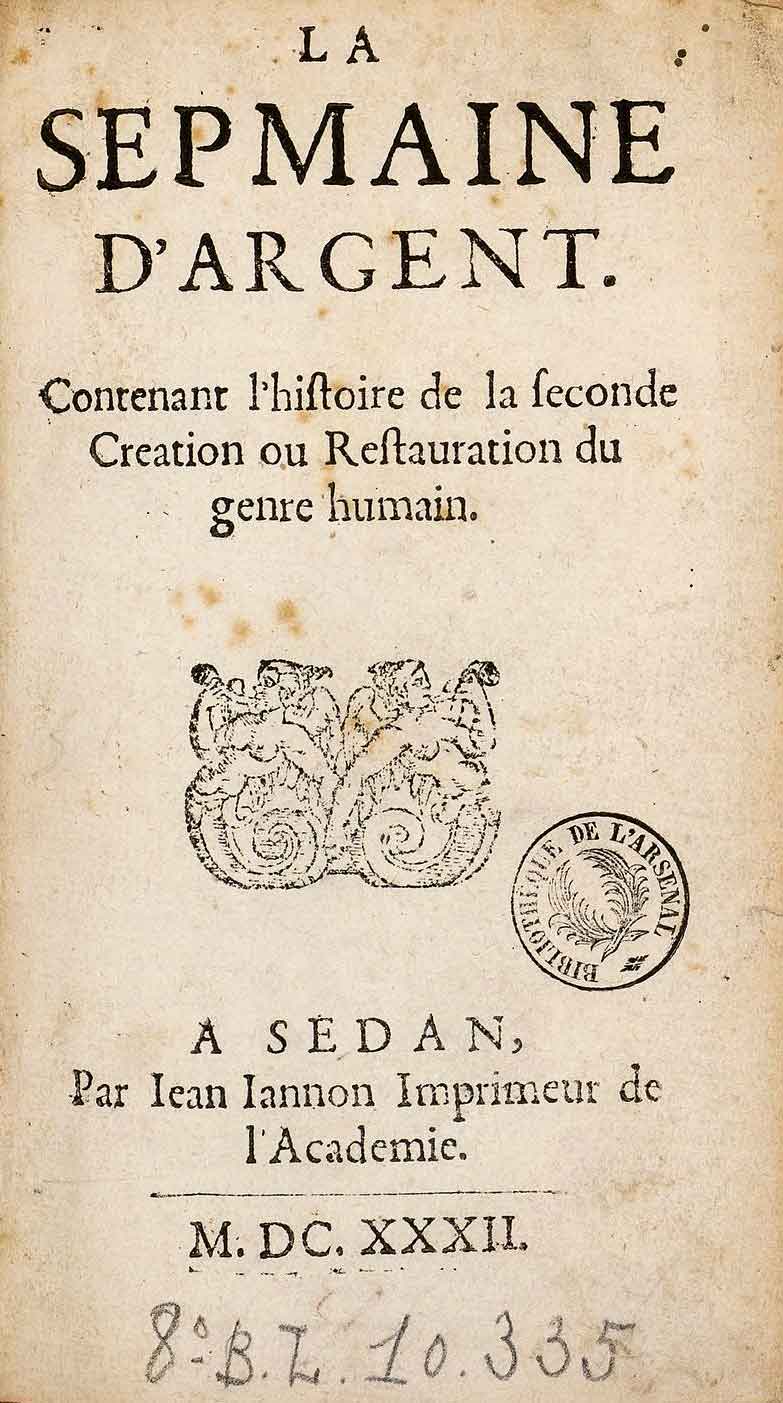
Jannon, Jean
Jean Jannon ist ein französischer Typograf, Buchdrucker, Buchhändler und Stempel- bzw. Schriftschneider. Geboren im April 1580 in der Romandie (Schweiz), vermutlich in Genf. Gestorben am 20. Dezember 1658 in Sedan in Frankreich. Typograf an der Akademie des protestantischen Fürstentums Sedan (und Raucourt). Alternative Schreibweisen seines Namens: Iean Iannon, Joannes Jannonus, Jean Janon und Joannes Janonus. 1)  2)  3)
Jean Jannon entwickelte die mutmaßlich von Claude Garamond (um 1498/99–1561) 1533 entworfene Französische Renaissance-Antiqua weiter, die um 1621/1622 unter dem Namen »Garamond-Schrift« europaweit bekannt wurde. 4) Jannons späte Renaissance-Antiquas werden als Übergangsformen zu den Vorklassizistischen Antiquas bewertet, die sukzessive in der ersten Hälfte des 17. Jahrhunderts aus der Renaissance-Antiqua entwickelt wurden.
Seine »Caractères de L’Université« – basierend auf seiner »Petite Sedanaise« aus dem Jahr 1621, was karikiert übersetzt »die Kleine aus Sedan« bedeutet, gelten gemeinhin als elegant und als handwerklich brillant geschnitten. Allerdings ist die These, wonach er diese Drucktypen nach dem »Goldenen Schnitt« (divina proportio) entwarf, nicht korrekt.
Jean Jannon war – wie bereits zuvor Antoine Augereau (um 1485–1534, Humanist, Typograf und Lehrmeister Garamonds) – Opfer der römisch katholischen Inquisition (13. bis 18. Jahrhundert, lat. »inquisitio« für »Untersuchung«). Viele Drucktypen von Jean Jannon wurden deshalb bis ins 20. Jahrhundert irrtümlich dem Pariser Schriftschneider und Typografen Claude Garamond zugeordnet.
Jan Jannon absolvierte eine Lehre als Buchdrucker in Genf und arbeitete als Geselle in Lausanne, Basel und Süddeutschland. Er beendete seine Ausbildung in Paris bei dem berühmten Buchdrucker, Verleger und Lexikograf Robert Estienne III. (um 1499/1503–1559), der 1550 zum Calvinismus 5)  konvertierte und mit seiner gesamten Offizin ins protestantische Genf emigrierte – insbesondere aufgrund der römisch katholischen Repressalien, beispielsweise der Zensur durch die Pariser Theologen der Sorbonne und dem einhergehenden Verkaufsverbot seiner kritisch kommentierten »Biblia«.
Haupttitel aus »La sepmaine d'Argent« von Jean Jannon aus dem Jahre 1632. Quelle: Bibliothèque nationale de France (Französische Nationalbibliothek).
Haupttitel aus »La sepmaine d’Argent« von Jean Jannon aus dem Jahre 1632. Quelle: Bibliothèque nationale de France (Französische Nationalbibliothek), online verfügbar unter https://gallica.bnf.fr/ark:/12148/bpt6k3141321 (27.9.2022).
In Sedan arbeitete Jean Jannon bis 1640 als Buchdrucker an der fürstlichen Akademie von Sedan, wo er vermutlich ab den 1610er Jahren auch an eigenen Drucktypen arbeitete, die auf der Typometrie der Garamond-Schriften bzw. den Schriften von Antoine Augereau 6) basierten.
Von 1640 bis 1645 Aufenthalt in Paris, wo er zunächst nach dem Tode seines Sohnes Antipas im April 1639, der ebenfalls Buchdrucker und Buchhändler war, als Schriftschneider und vermutlich auch als Kompagnon  des in Caen geborenen Buchdruckers Pierre de Cardonnel (1614–1667) arbeitete. Zeitgleich war Jannon Inhaber (oder Mitinhaber?) einer Offizin in Caen, dem Sitz der Generalität für die Basse-Normandie und eine Hochburg der Hugenotten (französische Protestanten, geprägt von der Lehre Johannes Calvins, 1509–1564).
Während seiner Schaffenszeit in Paris wurde Jean Jannon, der selbst Calvinist war, Anfang der 1640er Jahre Opfer der Repressalien von Armand-Jean du Plessis, Premier Duc de Richelieu (1585–1642), kurz »Kardinal Richelieu«.
Die Ursachen der Vergeltungsmaßnahmen waren unterschiedlich motiviert. Einerseits absolutistische und religiöse Motive – Kardinal Richelieu war u.a. Repräsentant des katholischen Klerus und Jannon protestantischer Drucker (Hugenotte) aus dem um 1642 annektierten Sedan – andererseits wollte Richelieu sicherlich, der 1640 die »Imprimerie Royale« auf Wunsch von König Ludwig XIII. (1601–1643) unter ihrem ersten Direktor Sébastien Cramoisy (1584–1669) gegründet hatte, Wettbewerber eliminieren.
Die ministeriale Administration Richelieus ließ deshalb im Zuge eines Inquisitionsverfahrens Jannon als Ketzer – im Zeitfenster des Krieges gegen das Fürstentum Sedan – verhaften, während gleichzeitig seine Druckwerkstatt und seine Werkzeuge zum Schneiden von Drucktypen in Paris und Caen konfisziert wurden. Kardinal Richelieu nutzte daraufhin Jannons enteignetes Drucktypenrepertoire für die Publikationen der Imprimerie Royale, u.a. auch für sein eigene Publikation »Les Principaux points de la foi de l’Église catholique défendus contre l’écrit adressé au Roi par les quatre ministres de Charenton (…)«. 7) Im Vorwort dieses Werks wird Schriftliebhabern insbesondere die Eleganz des kursiven Schriftschnitts bewußt.
Renommierte Fachleute, beispielsweise der Typograf Stanley Morison (1889 –1967) 8)  oder der Bibliothekar und Historiker James Mosley (*1935), 9) sind sich heute im Wesentlichen darüber einig, dass viele Repliken10)  Remakes11)  Klone12) Formvarianten 13)  und Mischformen 14)  auf der Typometrie von Jannons Drucktypen beruhen. 15)  So beispielsweise die
• American Garamond
• ATF Garamond
• Amsterdamer Garamond
• Italian Garamond
• ITC Garamond